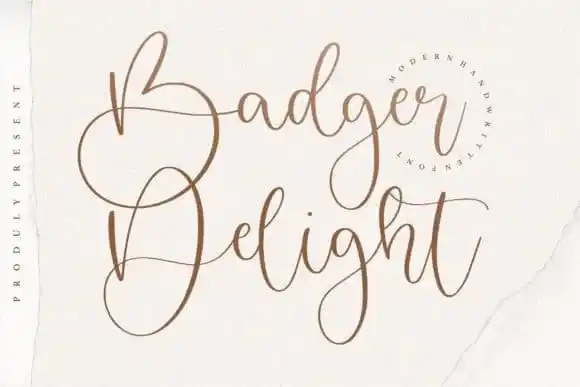
Badger Delight Script Font – Download Grátis
Introduzimos a Badger Delight Script Font – uma fonte script moderna que destaca-se por sua linha variável e suave, com toques clássicos e elegantes. Este recurso é especialmente útil para aqueles designers interessados em dar um toque de escrever à mão aos seus projetos. O Badger Delight Script Font possui uma variedade significativa de alternativas para letras minúsculas, incluindo swashes tanto no início quanto no fim das letras. Isso não só torna a fonte encantadora e impecável em qualquer projeto, mas também adiciona um toque único e personalizado. Idealmente projetada para uso em cartões de casamento, cartas de agradecimento, citações, cartazes de aniversário, logotipos, cartões de negócios e em qualquer outro design que necessite de uma pitada de escrita à mão. A Badger Delight Script Font é uma fonte de letras redondas inspirada na escrita à mão. Ela não apenas oferece a elegância e sofisticação esperadas em fontes script, mas também adicionará um toque autêntico ao seu design.